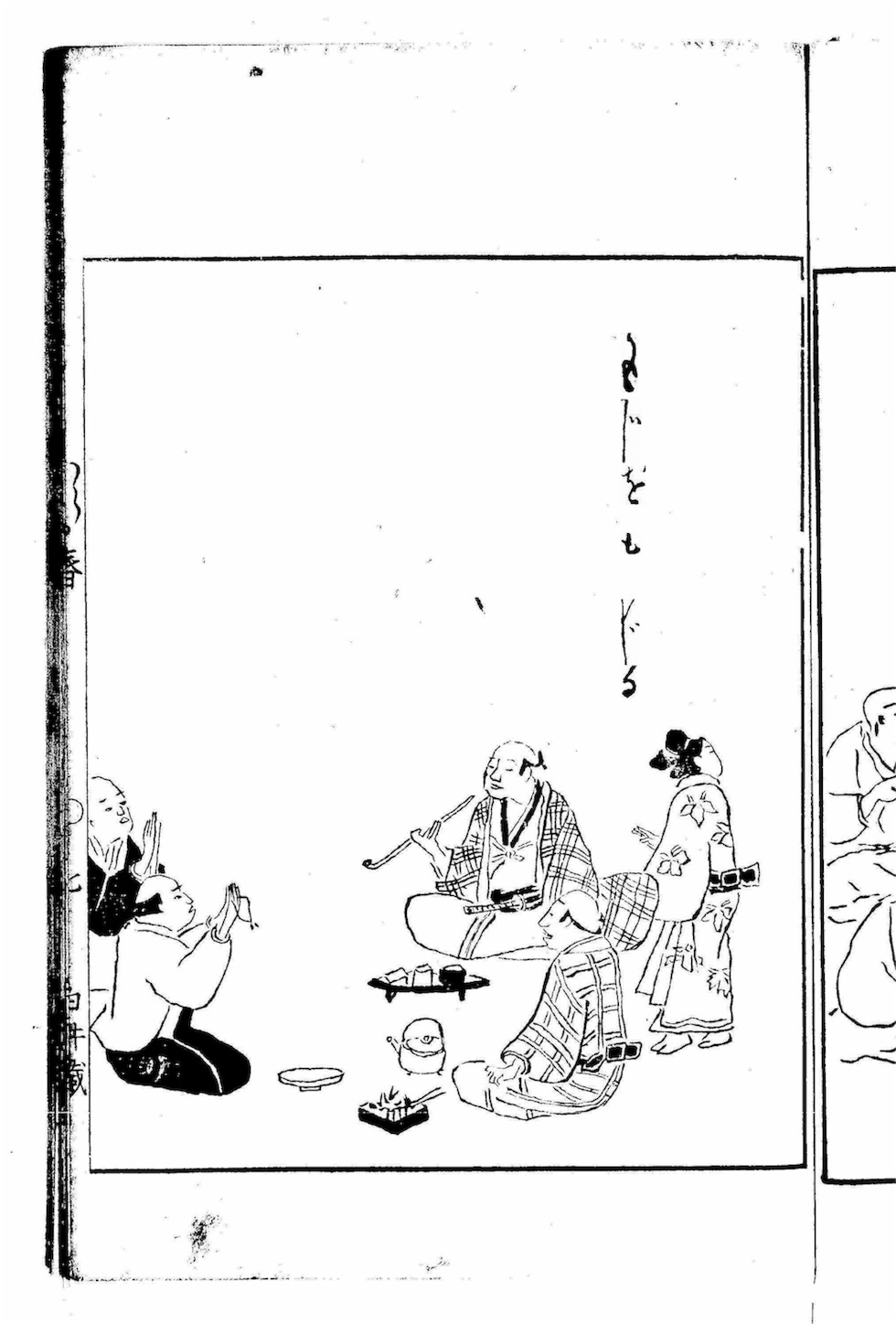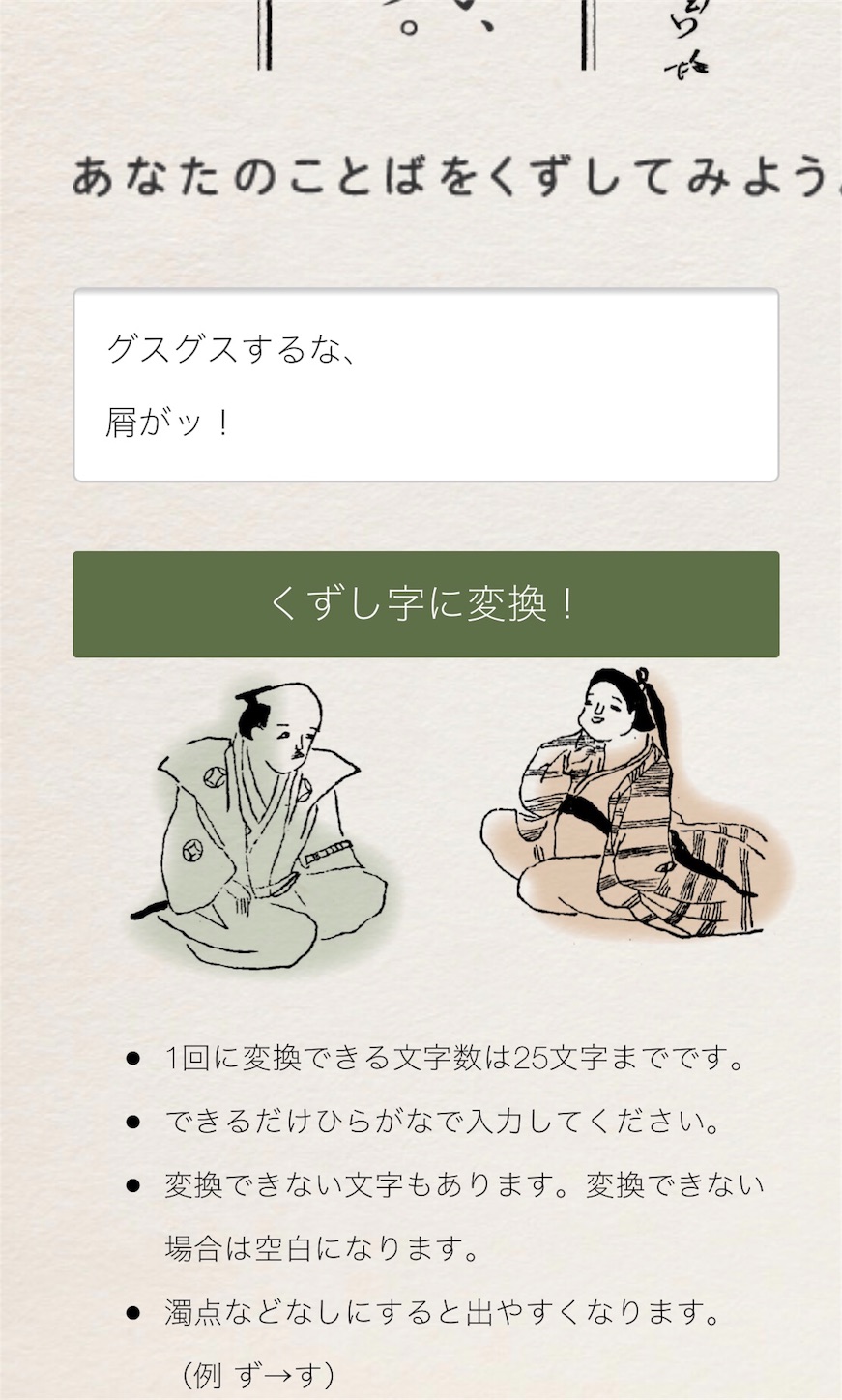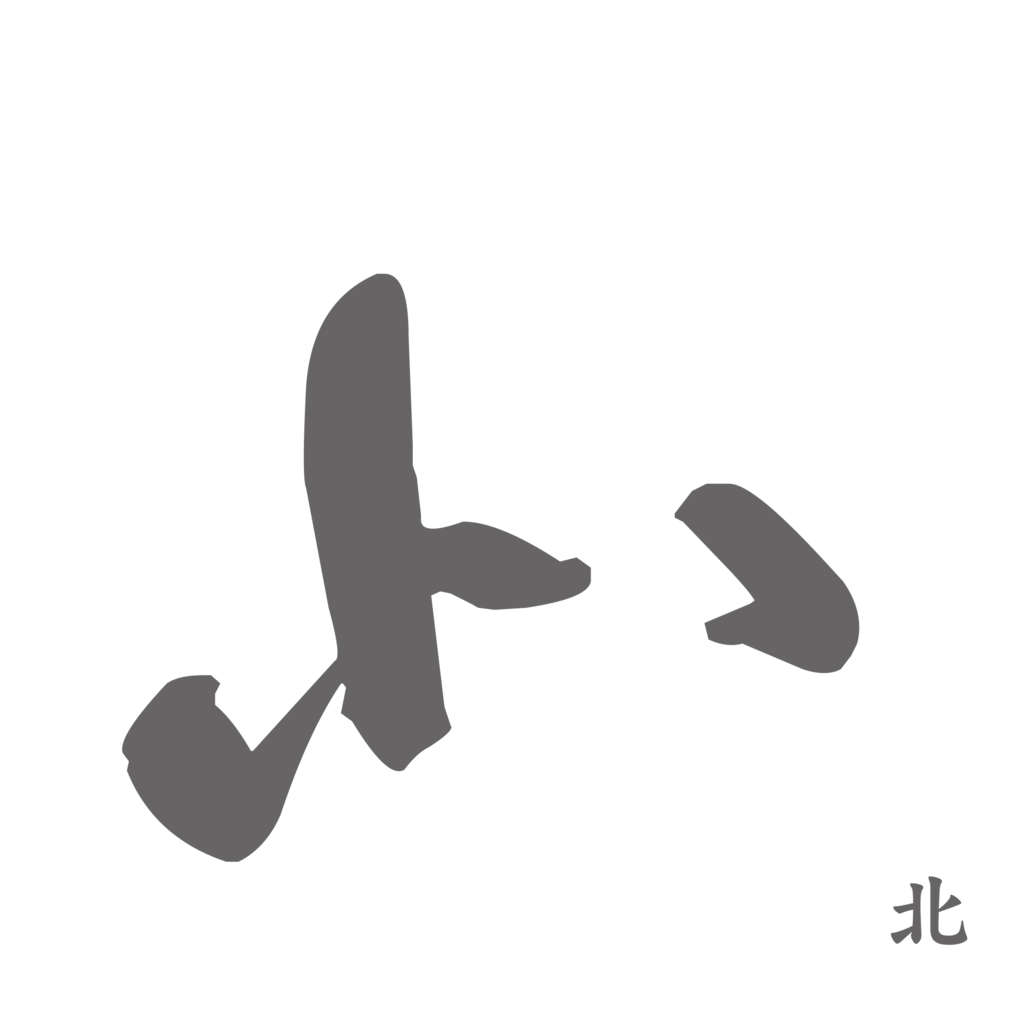
くずし字を生成できるツール「くずし字、いろいろ」とは?
10,000文字を超えるくずし字データベースをもとにして「くずし字」に変換できるサイト。
大学共同利用機関法人人間文化研究機構の国文学研究資料館と大学共同利用機関法人情報システム・研究機構の国立極地研究所による「オーロラ4Dプロジェクト」が、2018念4月26日に、くずし字を生成できるツール「くずし字、いろいろ」として発表。
読むのが難解すぎる「くずし字(崩し字)」
くずし字は草書とも呼ばれる書体で楷書の点画を省略した崩し書きの文字。
平仮名はまだ読めるが、漢字は難問すぎる。
下記はくずし字の書体で入力した漢字。
くずし字の書体からゴシック体に変換すると下記のようになる。
答えは、殺人事件 明治維新 馬耳東風 潜在意識
新元号「令和」くずし字(崩し字:草書体)体の書体見本
新元号「令和」くずし字(崩し字:草書体)体の書体見本。
やっぱり読めない…。
令和はおろか、旧元号を並べたものもさっぱり読めないのがくずし字。
下は明朝体に変換した文字。
くずし字を生成できるツール「くずし字、いろいろ」の特徴
「くずし字、いろいろ」は、webサイト上で入力したテキストが、1万文字をこえるくずし字データベースから、くずし字に自動変換され、それが記載された古典画像として生成される仕組みのツールになっている。この仕組みは人文学オープンデータ共同利用センターで公開されている「日本古典籍字形データセット」を活用したもの。1回に変換できるのは25文字までとなっている。また仕様上、できるだけひらがなで入力し、濁点などをなくすと出力されやすくなる。変換できない文字もあり、その部分は空白になる。
「くずし字、いろいろ」は、古文書に親しんで欲しいという思いから、人文学オープンデータ共同利用センター(CODH)で公開されているデータを活用して開発された。
「くずし字、いろいろ」で、文字を崩してみた!
公式では、「くずし字、いろいろ」の使用に適した状況として、昔の人の気持ちになってみたい、大切な人にラブレターを送りたい、オリジナルサインを作りたい時を挙げていた。それはさておき、「もじをもじる」というテキストでくずし字で、文字を崩してみた。
濁点に弱いと書いてあるが、「グズグズするな、屑がッ!」を崩してみた。
下記のような形になった。
2020年の漢字も読めない、それは密室・密着・密会でmeetsだよッ!
あいかわからず読めない2018年の今年の漢字R「災」を草書フォントにしてみた所、やっぱり読めない
今年の漢字Rは、その年の世相を表す文字を漢字一字を選んで公表する日本漢字能力検定協会のキャンペーン。、日本漢字能力検定協会の理事も務めていた清水寺の貫主である森清範により巨大な和紙に漢字一字が揮毫されるが、毎年のように漢字が読めないとネットをざわつかせている。
今年の漢字Rの2019年の漢字の予想「税」
2019年の「今年の漢字R」は前向きな言葉を期待したいが、増税の「税」になってしまうのでは…。苦しい時代が続く。
あいかわからず読めない2017年の今年の漢字R「北」を草書フォントにしてみた所、さっぱり読めない
まったく読めない2016年の今年の漢字R「金」を草書フォントにしてみた所、こちらも読めない
それが本書の企画意図である。
もちろん最低限のことは覚えなくてはならないが、
攻略のコツさえつかめば進歩は意外に早い。
ネット講座 「 くずし字を解説しよう! 」が
大人気の齋藤均先生のご協力のもと、
基礎の基礎にこだわって効率よく学べるポイントをまとめてみた。
くずし字の読みこなしはパズルや暗号解読に似ている。
のたくった謎の筆文字が意味のある言葉に
変わる瞬間は快感といっていい。
中高年の方には格好の脳トレにもなってくれるだろう。
本書は基礎の基礎という観点から、
平仮名の読解にテーマを絞った。
平仮名が読めるようになれば、
漢字にルビが振られた江戸期の
庶民向けの文書なら十分こなせる。
また漢字が混ざった古門書の読み取りにも自ずと道が開けるはずだ。
くずし字では一つの音にいくつもの種類( 異体字 )が設定される。
本書では異体字の数が限定されてくる江戸時代のものを中心に、
比較的登場頻度が高いものを齋藤先生にセレクトしてもらった。
なお異体字のパターンは、書道家の樋口英一氏に書き起こしていただいた。
読めると、文字を介して昔の人とつながれるなど
人生を豊かにしてくれる面もあるが、
それ以前に他人に真似できない知的な行為であり、
特技として人にほこっていいことだと思う。
この本で、あなたもくずし字マスターを目指そう。
山本明Profile●長野県生まれ。東京理科大学中退。歴史関連を中心に執筆活動を続け、『地図と写真から見える!古事記・日本書紀』(西東社)で、平成26年、「古事記出版大賞」を受賞した(本データはこの書籍が刊行された当時に掲載されていたもの)
くずし字解読辞典 普及版
児玉幸多編集による「くずし字解読辞典 普及版」が1993年3月1日に東京堂出版から発売されている。
すべての“くずし字”を起筆順に五つの部首に分けて配列した。くずし字に慣れない人たちのために同字異形を数多く掲出した。成語・熟語・慣用句などの例を豊富にあげて文書解読に便した。ひらがなと変体がなとを漢字同様に扱って該当箇所に挿入した。異体字・略体字・合成語句などもできるだけ掲げるようにした。付録に「カタカナ一覧」「扁旁くずし基準」「ひらがな・変体がなの解読」「字例によるくずし字検索一覧」を収録した。巻末に「音訓索引」を付し同一文字の異同を知るよすがとした。
くずし字用例辞典 普及版
児玉幸多編集による「くずし字用例辞典 普及版」が1993年3月1日に東京堂出版から発売されている。
草書如月の組見本
草書如月の欧文は丸ゴシック体になる。
草書如月の入手方法
草書如月はダイナコムウェアが開発・販売するダイナフォント(DynaFont)シリーズのフォント(書体)であり、有料フォントとなっている。
現在の入手方法としてダイナフォント製品をパッケージ化したTypeMuseumシリーズを購入で入手できる。
草書如月は下記のダイナフォント収録製品に収録されている。